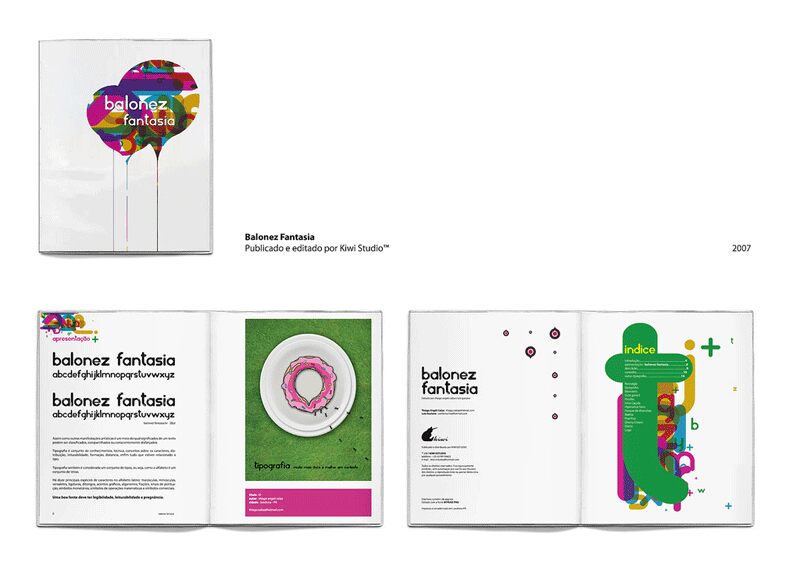
Balonez Fantasia to darmowy krój wyświetleniowy o „nadgryzionym” stylu, z pękatymi, zaokrąglonymi literami i małymi, ostrymi wcięciami, które przełamują jego gładką linię. Ciężkie krzywizny sprawiają wrażenie miękkich, balonowych kształtów, a ostre nacięcia przy podstawie nadają całości zabawny charakter, przypominający wycinanki.
Wykorzystaj ten bezpłatny font do projektów opakowań zabawek, słodyczy, plakatów dla dzieci, zaproszeń na imprezy i radosnych tytułów. Szerokie, proste formy śmiało niosą krótkie słowa, a powtarzające się nacięcia tworzą odpowiedni rytm wizualny dla krótkich nagłówków, nie przytłaczając liter.